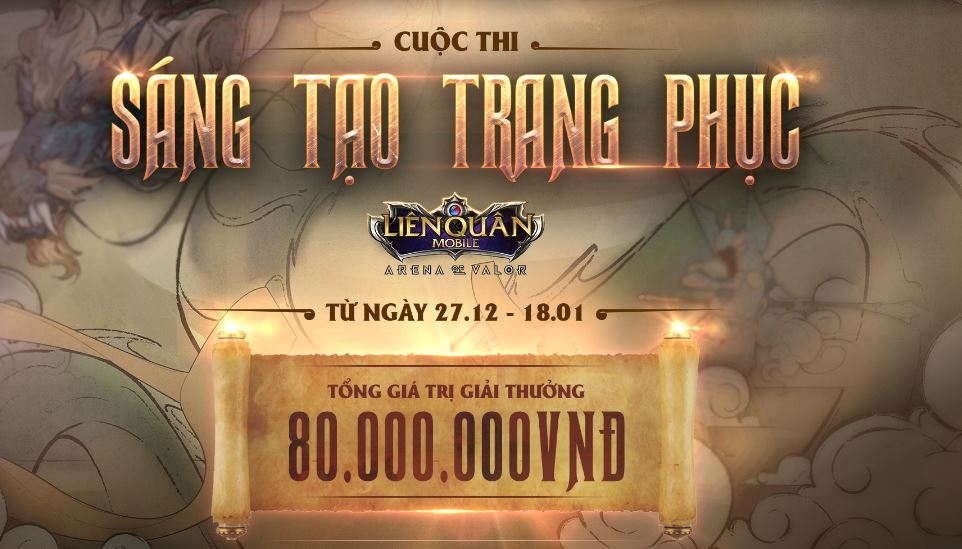
Font chữ liên quân là gì? Lợi ích khi sử dụng font chữ trong thiết kế truyền thông quảng cáo
Liên Quân Mobile là một tựa game yêu thích của đông đảo game thủ trên thế giới. Trong game, người chơi được thể hiện cá tính của mình thông qua nhiều cách. Trong đó, cách đơn giản nhất là sử dụng font chữ liên quân để tạo sự khác biệt. Việc đổi font chữ, màu chữ trong Liên Quân Mobile sẽ giúp nhân vật, giao diện chat của bạn thêm phần ấn tượng với những người chơi khác.
Khái niệm về font chữ liên quân?
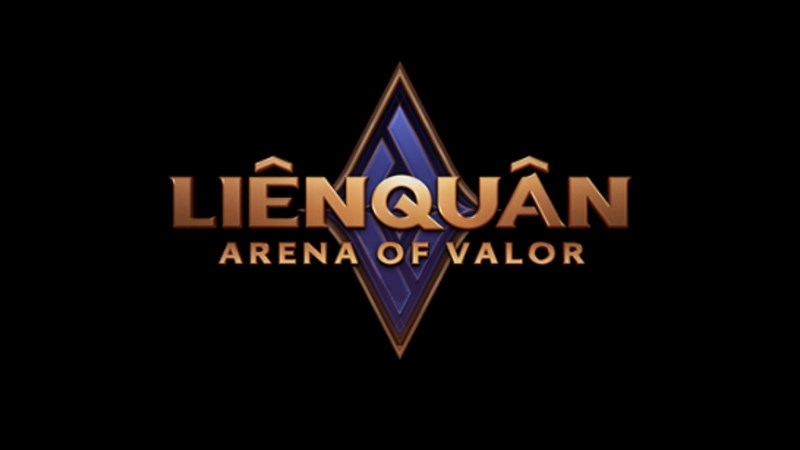
Font chữ liên quân là font chữ được sử dụng trong trò chơi Liên Quân Mobile. Font chữ không chỉ đem đến tính nhất quán và thẩm mỹ cho trò chơi mà còn tạo nên sự cá nhân hóa và nâng cao tính nhận diện nhân vật, trang phục hay bảng xếp hạng trong game.
Các loại font chữ liên quân thông dụng
Font chữ liên quân được chia thành nhiều loại font khác nhau nhưng phổ biến có 3 loại font sau:
Font chữ liên quân chính thức trong game Liên quân Mobile
Font chữ chính thức của game được thiết kế đặc biệt mang lại tính đồng nhất cho toàn bộ trò chơi. Font được sử dụng khi viết tên game, menu, hướng dẫn trò chơi và một số mục đích khác.
Font chữ liên quân cho bảng xếp hạng và trang phục trong game
Sử dụng các font chữ liên quân phù hợp trong trang phục và bảng xếp hạng khi chơi game Liên Quân Mobile sẽ làm tăng tính thẩm mỹ và tính độc đáo, sáng tạo. Đồng thời, font chữ sẽ thể hiện điểm khác biệt của từng người chơi.
Font chữ liên quân được tạo bởi game thủ
Điểm thú vị của font chữ liên quân là người chơi có thể tạo ra các font chữ riêng trong khi chơi game. Các font chữ được tạo từ các công cụ online hoặc tải xuống và cài đặt trong thiết bị của bạn. Mỗi game thủ có thể sáng tạo cho mình những font chữ riêng để tạo nên sự đa dạng và thể hiện cá tính riêng.
Điểm khác biệt của font chữ liên quân
- Hiệu ứng nghệ thuật: Font chữ liên quân thường được thiết kế với các hiệu ứng nghệ thuật như ánh sáng, đổ bóng tạo hiệu ứng thị giác cao. Điều này giúp font chữ trở nên bắt mắt và nổi bật trên màn hình.
- Kiểu chữ độc đáo: Font có nhiều biến thể từ chữ in đậm mạnh mẽ đến chữ viết tay nhẹ nhàng. Mỗi kiểu chữ mang đến cảm xúc khác nhau thể hiện tính độc đáo của font chữ này.
- Tính linh hoạt cao: Font chữ liên quân được sử dụng cho nhiều mục đích khác nhau trong game như đặt tên và viết tiểu sử nhân vật, tạo các ký tự đặc biệt ở giao diện khung chat,... Người chơi có thể thay đổi kích thước, màu sắc font chữ để thể hiện cá tính của mình.
- Phối màu sắc sáng tạo: Font chữ được kết hợp với các màu sắc sáng tạo, tương thích với bối cảnh và tông màu chủ đạo của game Liên Quân Mobile. Việc sử dụng màu sắc độc đáo giúp tạo ra sự nổi bật và nhận diện dễ dàng.
- Biểu tượng và ký hiệu đặc biệt: Font chữ thường đi kèm với các biểu tượng và ký hiệu đặc biệt giúp nhấn mạnh các từ hoặc thông điệp quan trọng.
- Tương thích với đa nền tảng: Các font chữ tương thích với nhiều nền tảng thiết bị khác nhau, không bị vỡ chữ, lỗi font giúp cho trải nghiệm người chơi mượt mà, thú vị.
Vai trò của font chữ liên quân trong game Liên Quân Mobile
Font chữ trong game Liên Quân Mobile đóng vai trò tăng trải nghiệm người chơi, tạo sự thú vị, hấp dẫn trong mỗi trận đấu. Các loại font chữ liên quân được thiết kế đặc biệt để thể hiện tính đặc sắc của trò chơi, tăng nhận diện nhanh chóng cho các gamer. Lựa chọn font chữ phù hợp sẽ giúp người chơi có thể đọc hiểu thông tin trên màn hình một cách dễ dàng nhất như tên nhân vật, các chỉ số, thông báo trong game,...
Font chữ liên quân được thiết kế phù hợp với phong cách của game. Ví dụ, bối cảnh của game là cổ điển có thể sử dụng font chữ vintage nhằm mang lại sự hài hòa. Ngoài ra, font chữ cũng có thể tạo cảm xúc và nâng cao trải nghiệm với người chơi game. Cụ thể, sử dụng font chữ mạnh mẽ, kích thước lớn để thông báo quan trọng hay font chữ nghệ thuật tạo nên điểm nhấn,...
Có thể nói, font chữ liên quân không chỉ là “nguyên liệu” tạo nên sự hấp dẫn cho game mà còn đem đến trải nghiệm chơi game thú vị và tương tác tốt cho cộng đồng người chơi.
Lợi ích của font chữ liên quân trong ngành quảng cáo
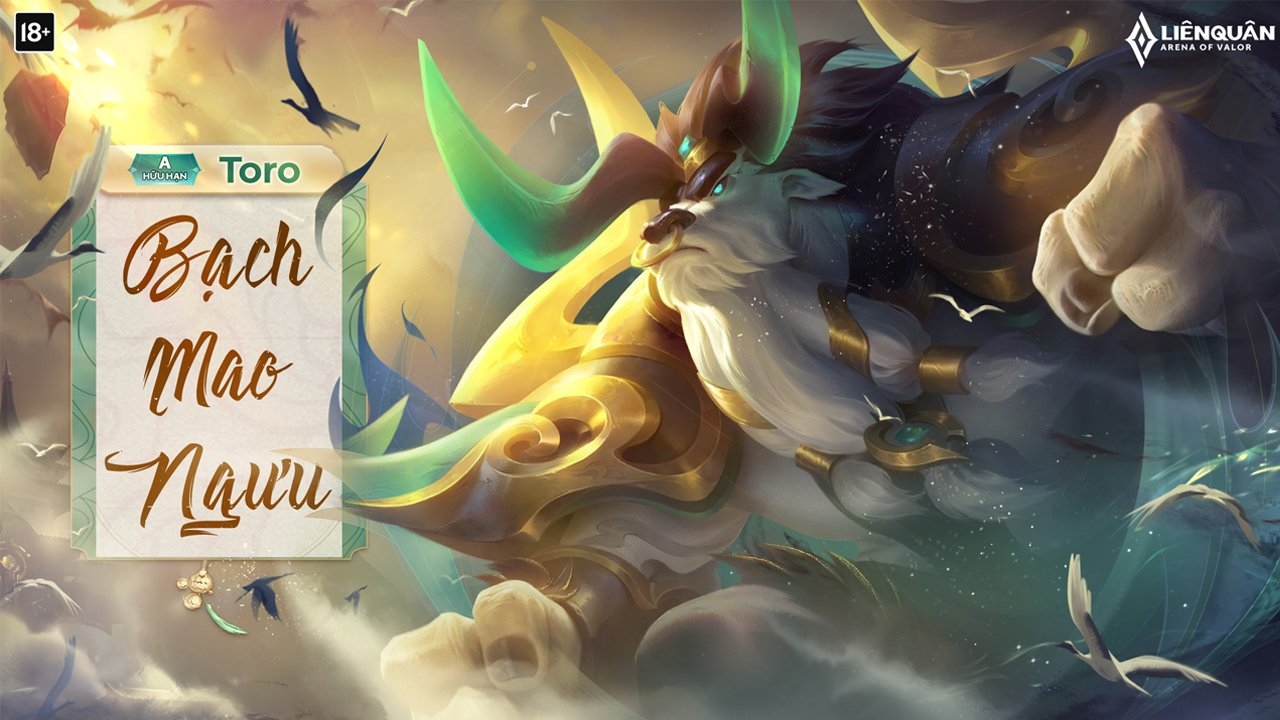
Font chữ liên quân được các doanh nghiệp quảng cáo ứng dụng rộng rãi để gây ấn tượng mạnh với khách hàng. Trong các chiến dịch quảng cáo của doanh nghiệp, font chữ liên quân sẽ mang lại những kết quả sau:
- Tạo sự liên kết với cộng đồng: Sử dụng font chữ liên quân có thể giúp doanh nghiệp xây dựng sự liên kết với cộng đồng game, đặc biệt là những game thủ yêu thích trò chơi này. Việc nhận biết font chữ quen thuộc có thể kích thích sự chú ý từ người chơi game.